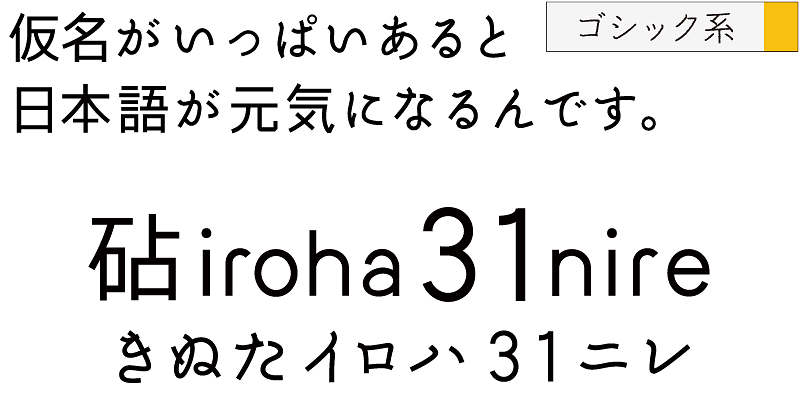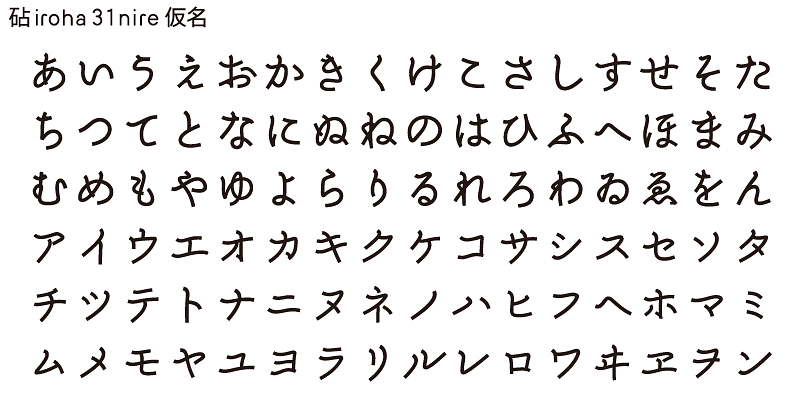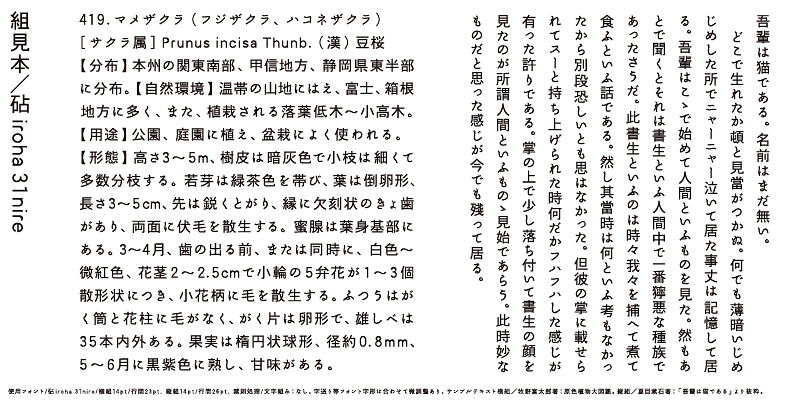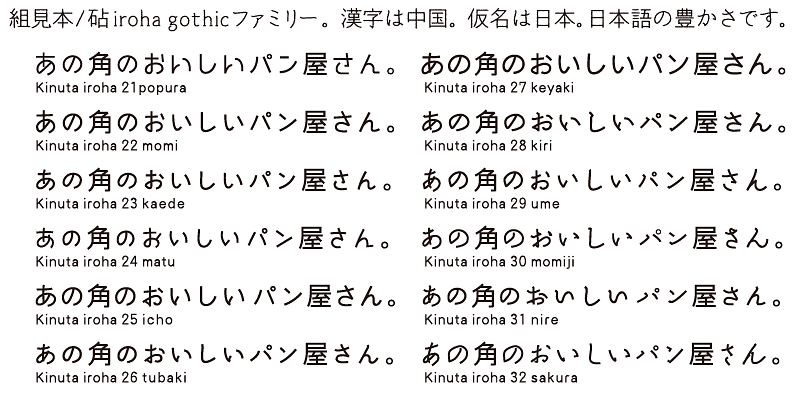
Die Kana-Zeichen von Iroha 31nire basieren auf einer Version von MaruminOld im gotischen Stil. Mit dem Aussehen einer Pinselschrift hat sie ein kompaktes und niedliches Design.
Alle Iroha-Varianten haben die gleichen ideografischen (Kanji-)Zeichen. Die Kanji-Zeichen von Iroha sind mit linearen Strichen und einfachen Strukturen gestaltet. Es gibt 12 Kana-Varianten.
Ein Merkmal der japanischen Sprache sind ihre Kana-Silbenzeichen. Kana-Zeichen wurden in Japan erfunden, um japanische Laute darzustellen und aus China importierte Texte ins Japanische zu übersetzen. Kana-Zeichen werden benötigt, um japanische Wörter und Ausdrücke aus Kanji (chinesischen ideografischen Zeichen) zu erstellen. Auch wenn es Zweideutigkeiten gibt, zeigen diese Wörter und Ausdrücke die Wärme und Sanftheit des Lebens der Menschen, die in dem kleinen und dicht besiedelten Japan leben.
Kinuta Font Factory ist davon überzeugt, dass Kana-Zeichen der Ursprung auf Japanisch geschriebener Wörter sind, und wir glauben, dass die Optimierung von Kana-Zeichen japanische Texte attraktiver macht. Im Durchschnitt bestehen 60 % der japanischen Texte aus Kana-Zeichen – ändert sich die Form dieser Zeichen, verändert das auch das visuelle Erscheinungsbild des Textes. Die Möglichkeiten des typografischen Ausdrucks mit einfachen, dynamischen und kurvenförmigen Kana-Zeichen sind enorm und die Üppigkeit japanischer Texte hängt von Kana-Zeichen ab. Aus diesem Grund bietet Kinuta Font Factory viele Variationen von Kana-Schriftarten an.